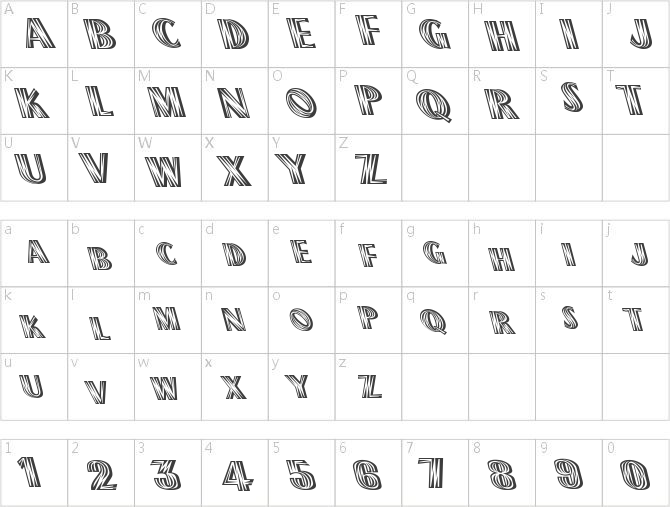
Chili Pepper-Extra Bold Lefty
Chili Pepper-Extra Bold Lefty介绍
Chili Pepper-Extra Bold Lefty字体字库是一款让人赏心悦目、百看不厌的英文字体,适合各类广告和产品包装设计应用,字体大小0.1MB,格式为ttf字体,上传用户是ㄚòひ慬偶鰢,作者/版权方为未知